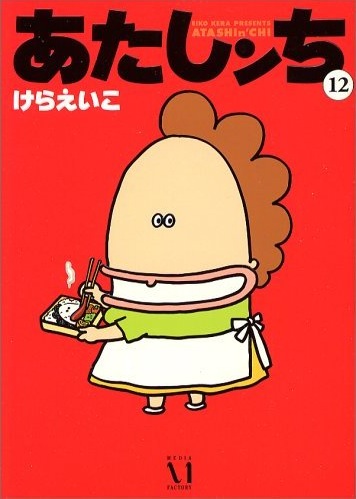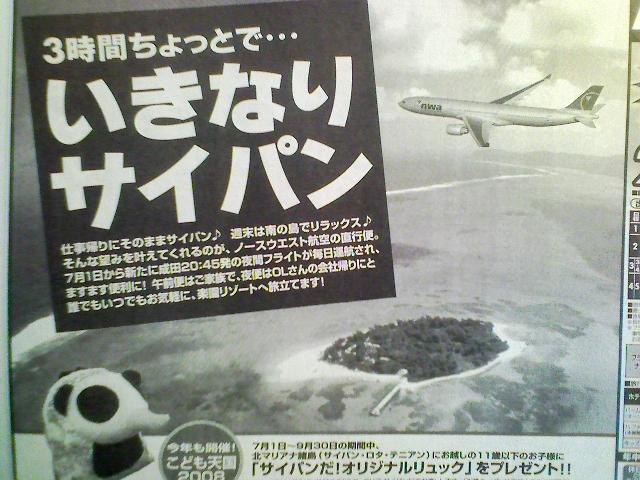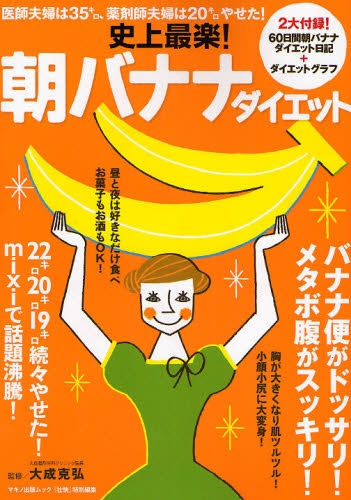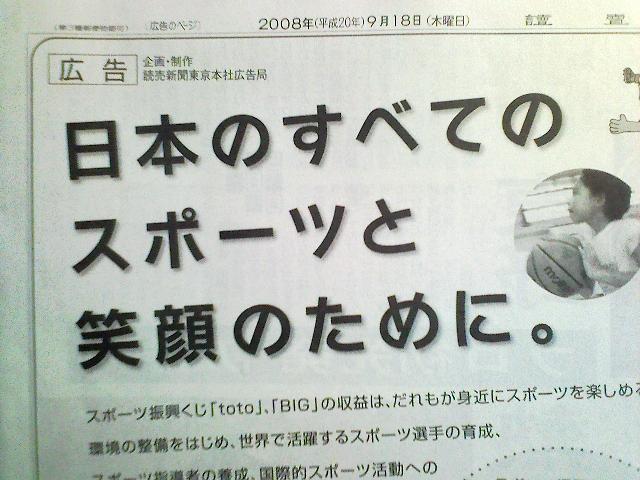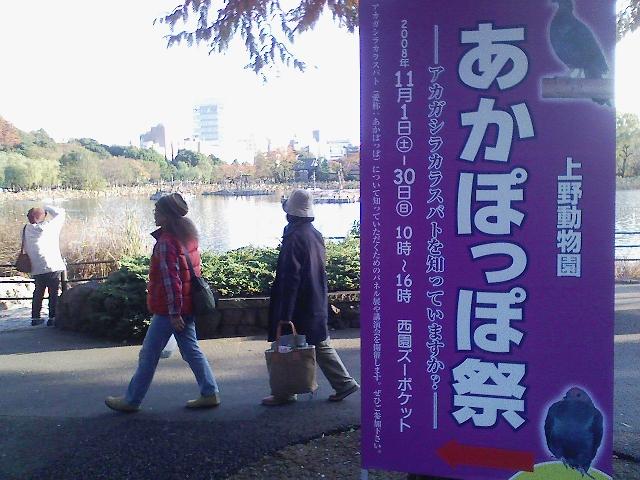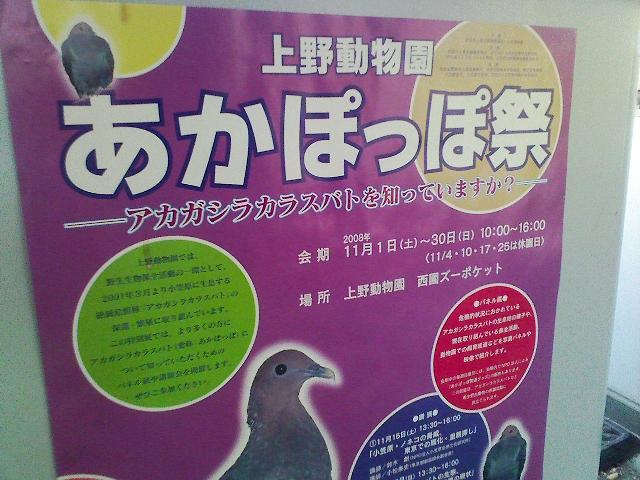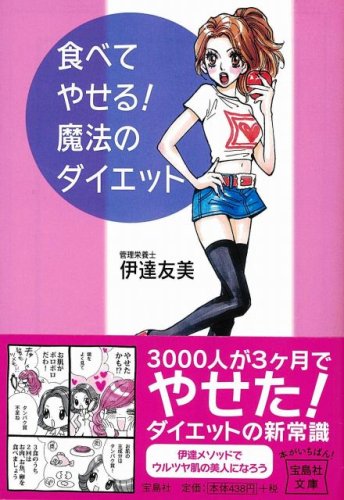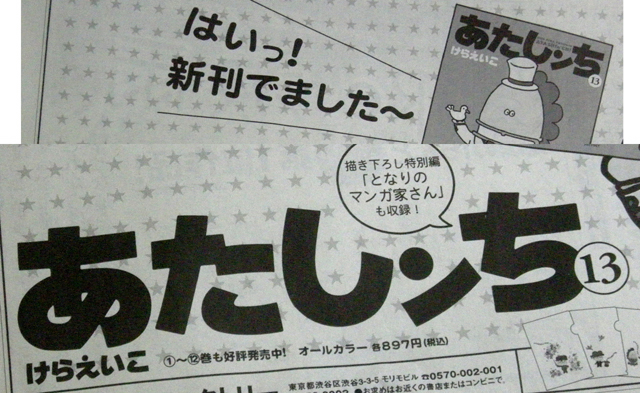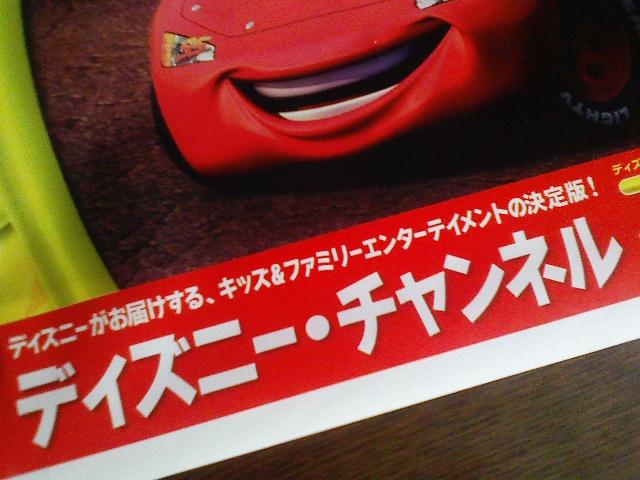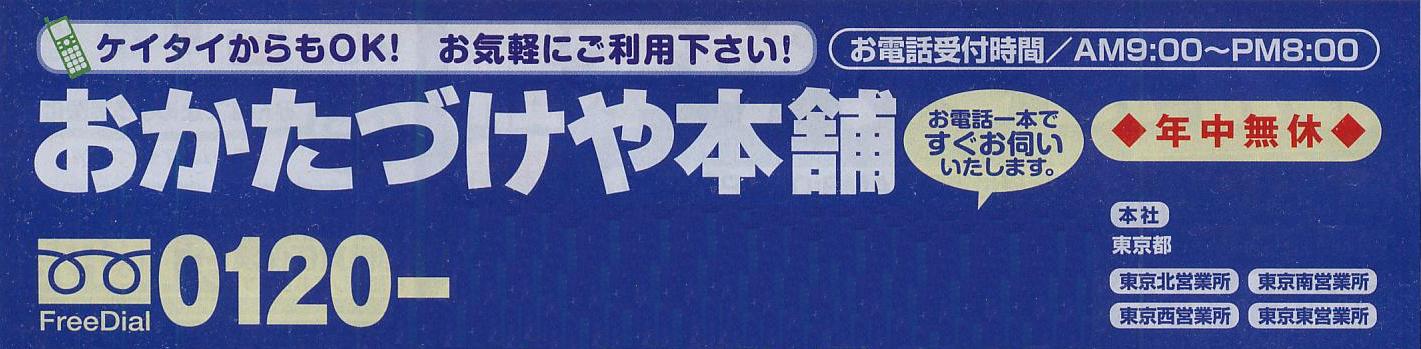
駅構内のポスター さとうゆたか
光の具合が悪く、反射を避けてこんな写真になりました。
本の表紙 さとうゆたか
書名:トッカン(特別国税徴収官)
著者:高殿円
発行:早川書房
本の表紙 さとうゆたか
書名:おっぱいとトラクター
著者:マリーナ・レヴィツカ
翻訳:青木純子
発行:集英社
カラーの新聞広告 さとうゆたか
「夏休みはユニバーサル・スタジオ・ジャパンに行こう!」の部分。
漢字(夏休行の文字)に、丸ゴシック系の書体が使われているのは珍しいと思う。
進学塾の広告 さとうゆたか
進学塾の新聞広告です。
イベントポスター さとうゆたか
昨年も載せた記憶がある…。
ウチの近所の催し物です。
新聞広告 さとうゆたか
昨日の新聞。
漫画雑誌の表紙 さとうゆたか
女性向けの漫画雑誌です。
なぜか「だ」の文字だけ傾いていますが…。
カーシェアリング さとうゆたか
新聞に折り込まれていたチラシ。
冬はやっぱり巨…… さとうゆたか
漫画雑誌の目次ページ?